今回は、カレン・チェン(Karen Cheng)著、白井敬尚 監修、井原恵子 翻訳の『デザインワークにすぐ役立つ欧文書体のルール』を紹介します。
こちらは2006年に『Designing Type』として出版された本の日本語翻訳版です。
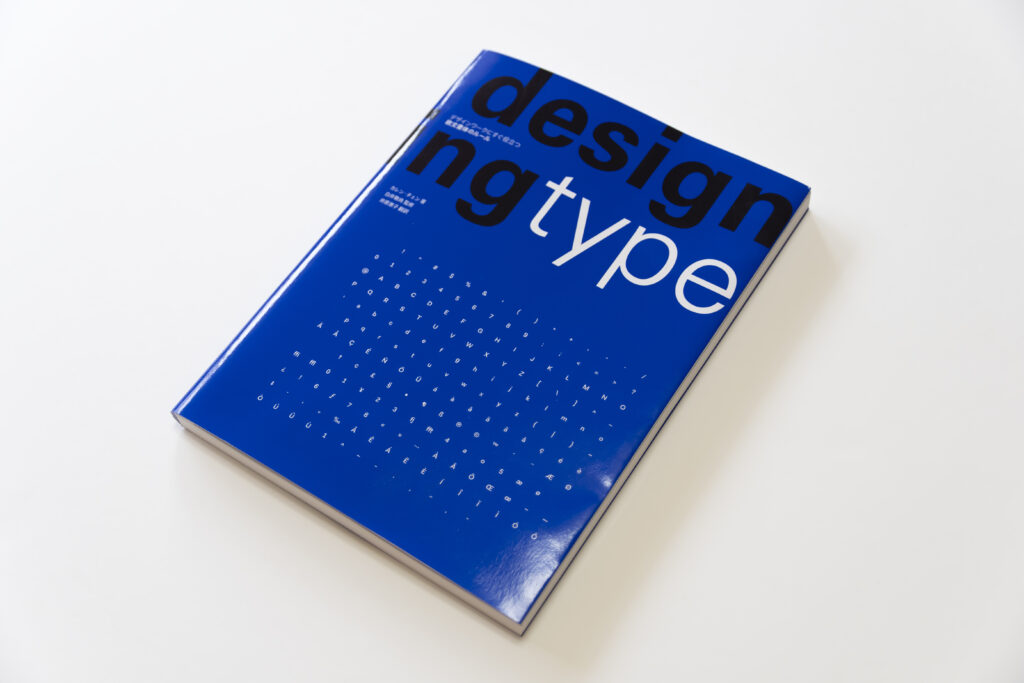
欧文書体の歴史や書体制作の基礎知識がまとめられています。欧文書体のデザインには、大文字・小文字・数字・記号などカテゴリーの異なる文字群を一つの書体として成立させ、読みやすい書体にするための様々な工夫がなされています。書体のデザインや用途によって制作方法も変わってきますが、この本では欧文書体制作に必要な基本的なルールが多くの図版と実際の書体での例とともに初心者にも分かりやすく解説されています。欧文書体制作に興味を持っている方にはもちろん、使う方にも役立つ情報が満載の一冊です。
私が書体デザインを一緒に学んだ海外の友人たちの中にも、学生時代にこの本を手にとったという人は多いです。欧文書体関連の書籍で日本語版が出版されているものは数少ないので貴重な一冊だと思います。欧文書体を作ってみたいけれどどこから始めたら良いかわからない、という方にはこちらの本をお勧めします。
また、日本語版の書籍には本文書体としてタイププロジェクトのTP明朝とTPスカイ、キャプションにはTPスカイ コンデンスが使用されています。(欧文部分はQuadraatとQuadraat Sans)
図版が多く使用される場面でキャプションにTPスカイコンデンスを使用することで、テキストがコンパクトにまとまり図版とキャプションの情報が見やすく整理されています。
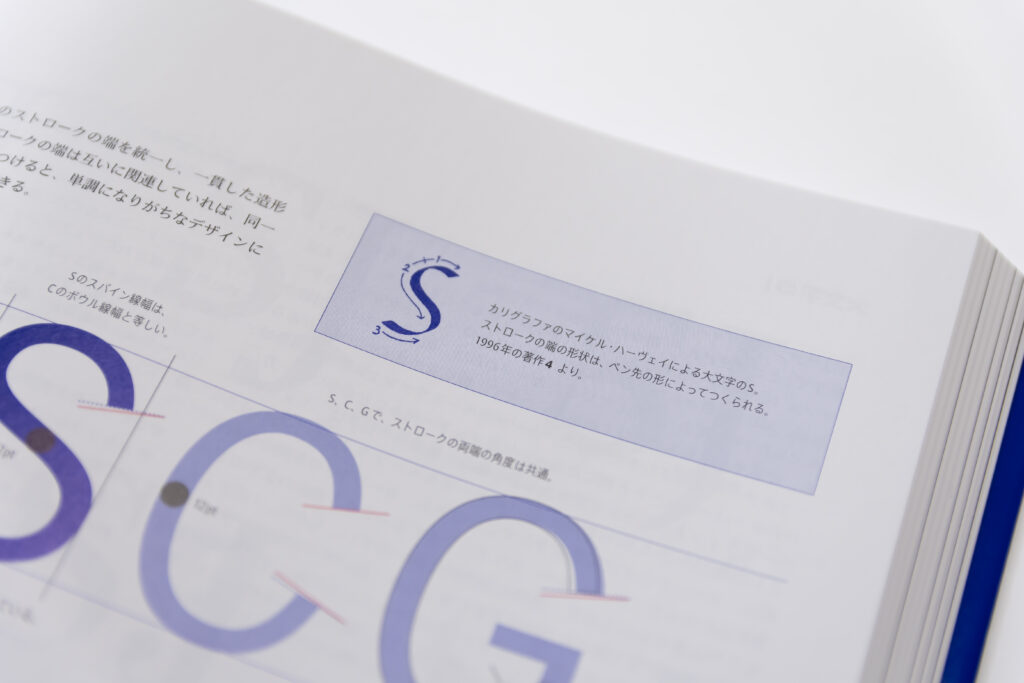
書籍情報:
日本語翻訳版
『デザインワークにすぐ役立つ欧文書体のルール』
著者:カレン・チェン
監修:白井敬尚
翻訳:井原恵子
発行:グラフィック社
英語版
『Designing Type』
著者:Karen Cheng
発行:Yale University Press